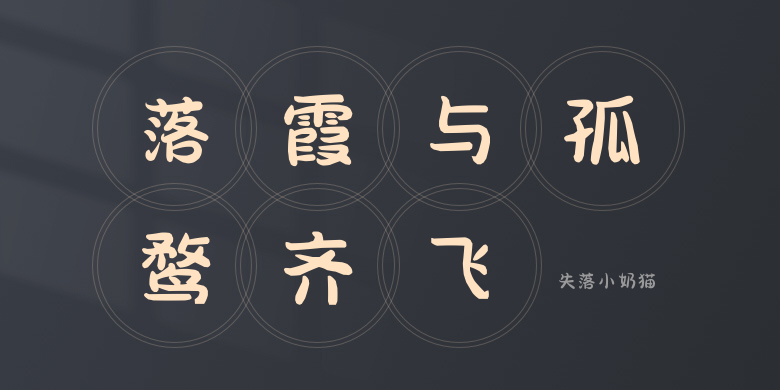
失落小奶猫
失落小奶猫,这款字体结构工整、笔画清晰,兼顾美观与易读性,适用于标题、正文、海报、包装、LOGO 等多种场景。字形优雅稳定,风格百搭耐看,适配日常排版与创意设计,让文字呈现更舒适、更具质感。失落小奶猫一笔一画,皆是细节,以均衡的比例、流畅的线条打造舒适视觉体验,字形端正大气,风格简约现代。无论是商业设计、品牌宣传还是日常排版,都能轻松驾驭,让文字更有格调与力量。失落小奶猫字体下载。